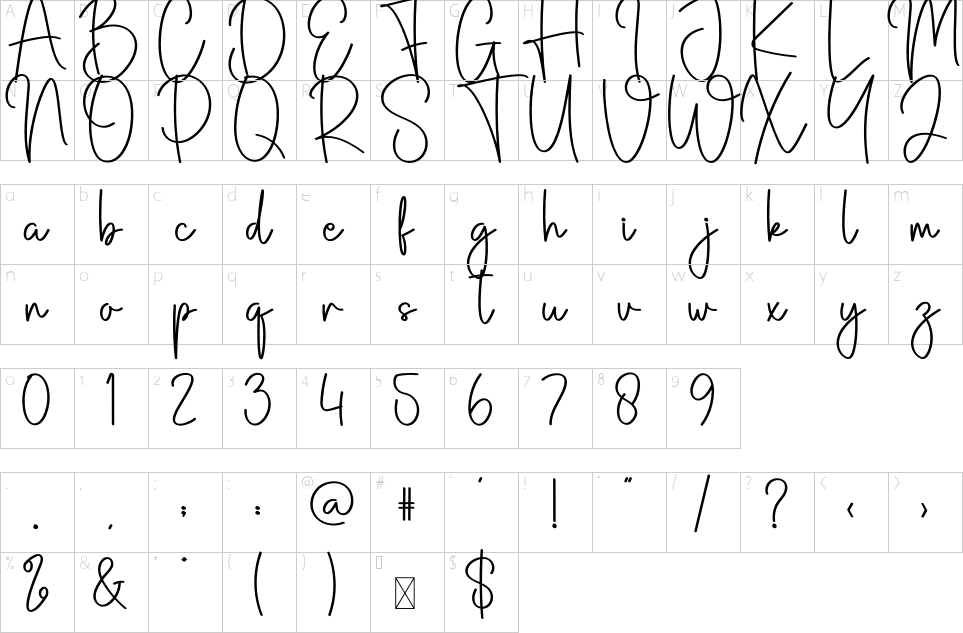
Giovany Signature Font
A fonte Giovany Signature é uma elegante escolha para qualquer projeto que exige sofisticação e personalidade. Desenhada pelo designer scratchones, essa fonte foi projetada pensando no detalhe e na perfeição do tipo de letra. Com seu design cuidadosamente elaborado, a Giovany Signature oferece um equilíbrio perfeito entre clássico e moderno, tornando-a uma opção ideal tanto para aplicativos empresariais quanto para ambientes mais criativos. Ela foi descarregada 219 vezes, o que prova seu valor como fonte de qualidade. Se você busca incorporar um toque único e sofisticado em seus projetos digitais, Giovany Signature pode ser sua escolha perfeita. Descubra agora mesmo a sensação única dessa fonte de alta qualidade que vem sem custo adicional.
Mapa de caracteres da fonte Giovany Signature Font